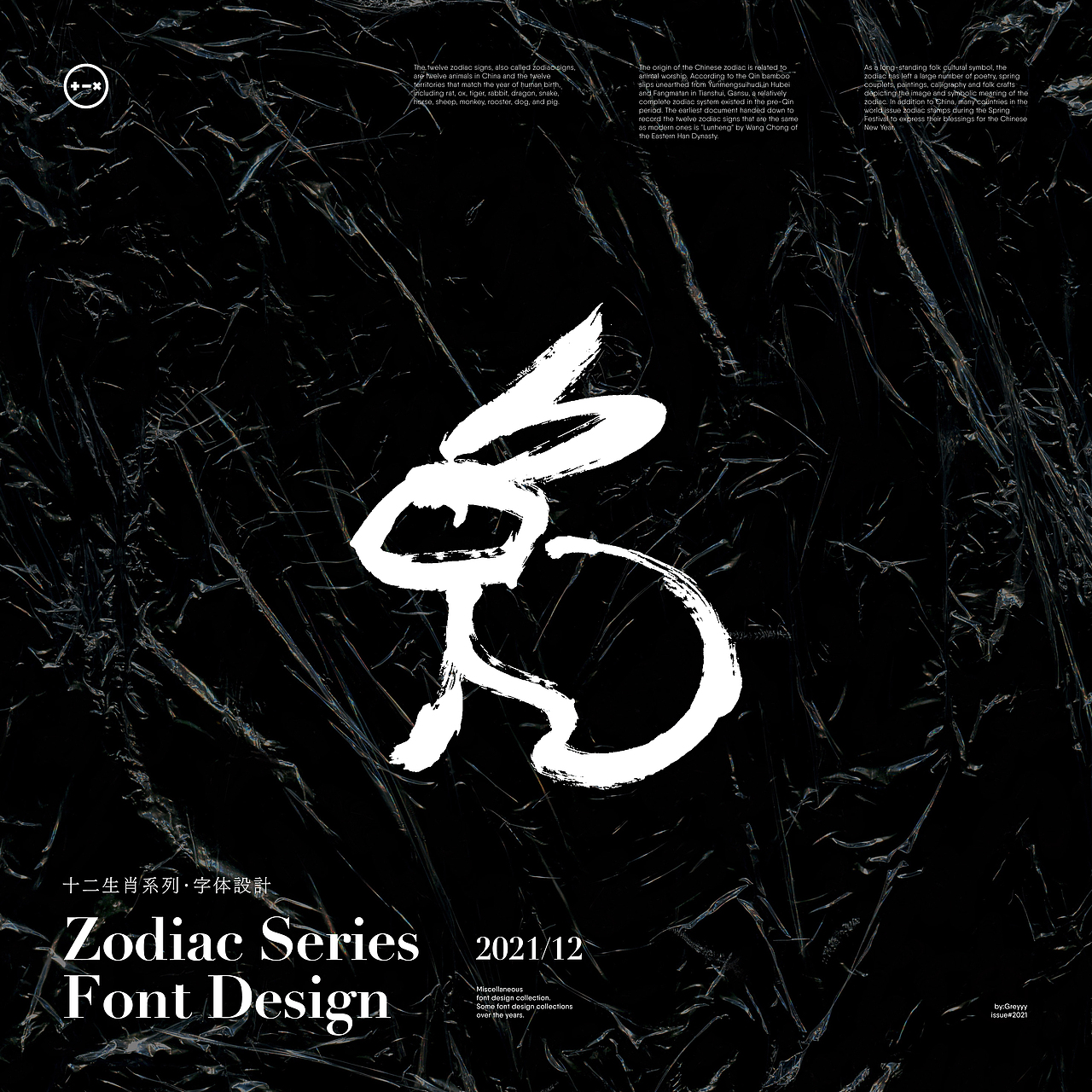
十二生肖|字体设计
这套系列字最开始原本只有一个「鼠」,后来想着干脆全做了,才有了后面剩余的11个生肖。原本希望这套字能在看出文字笔画走向的同时,展现出一个完整的动物身体的形象——关键是要灵动。但是最终还是没有达成理想效果就是了哈哈。
其实做到差不多一半的时候,偶然间发现了《12生肖形意字》这本老书,看见了前辈们做出的更加活灵活现的造型。当时真是巨尴尬,因为难免会有点相似之处,一时间不知道应该继续还是停止。后来在一位老师的鼓励下还是决定做完,至少也能提升个人能力,勉强完成了这一系列字体设计。
ps:这套字完全是用笔画拼接而成,并非书写出来的。